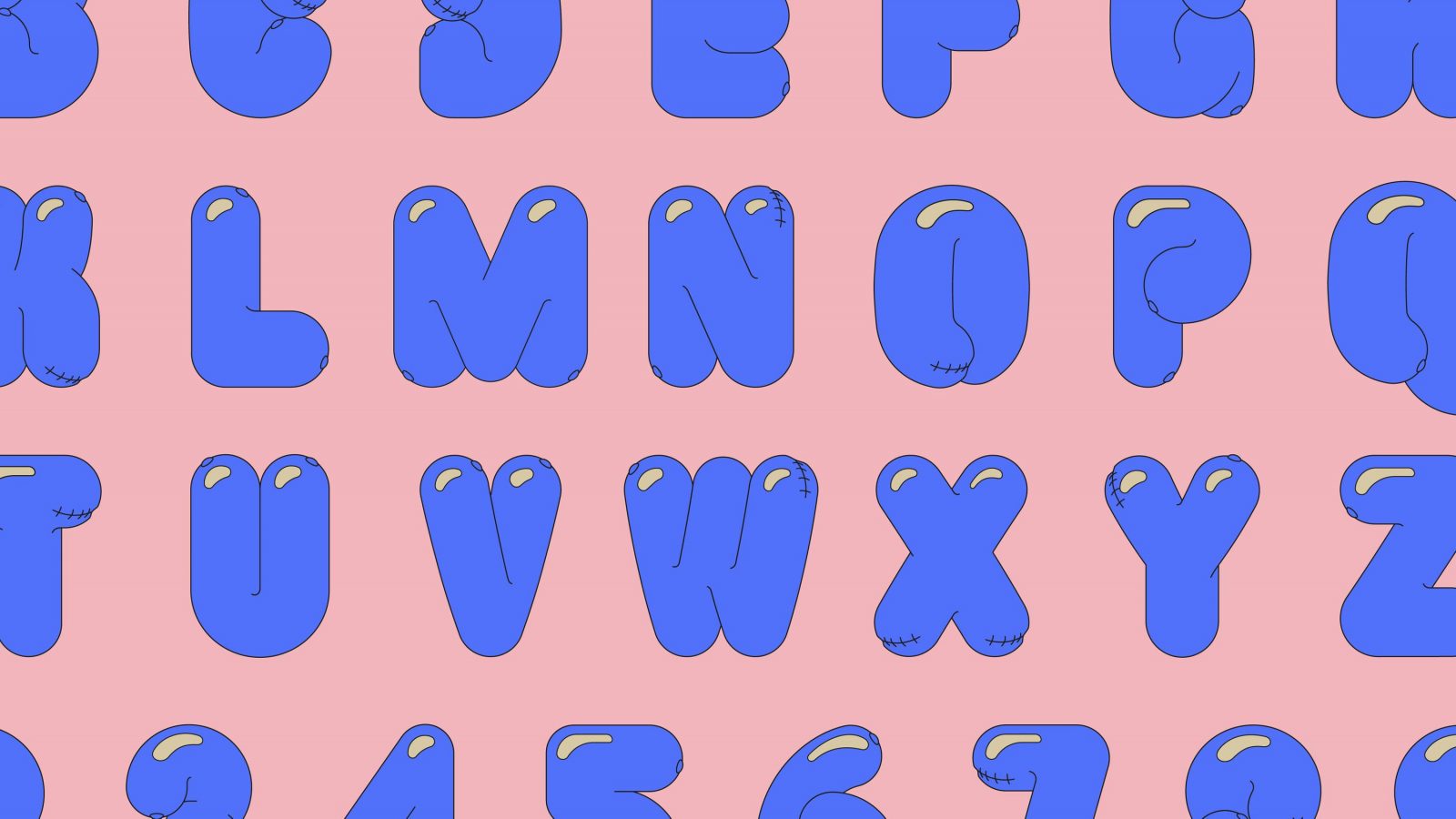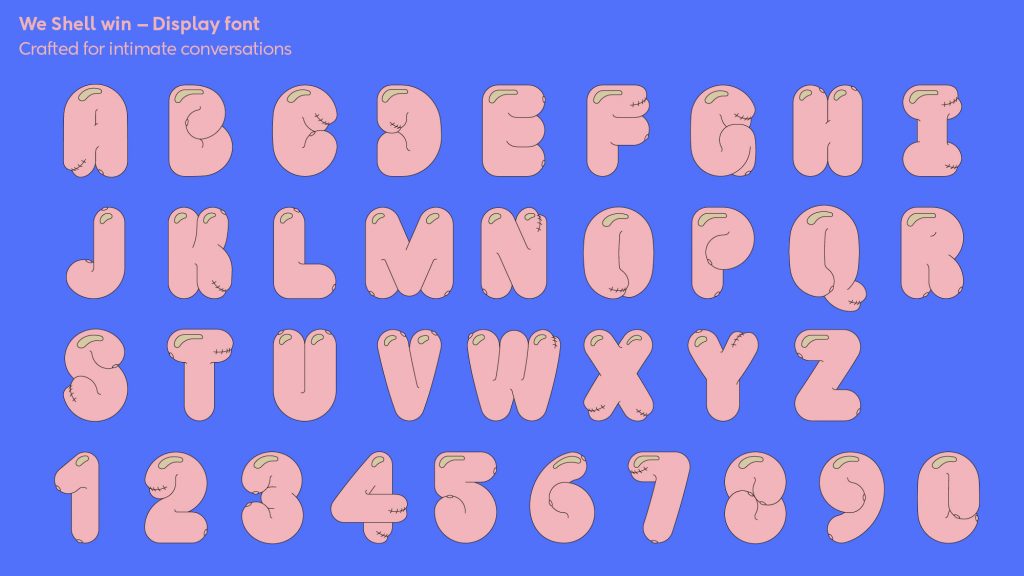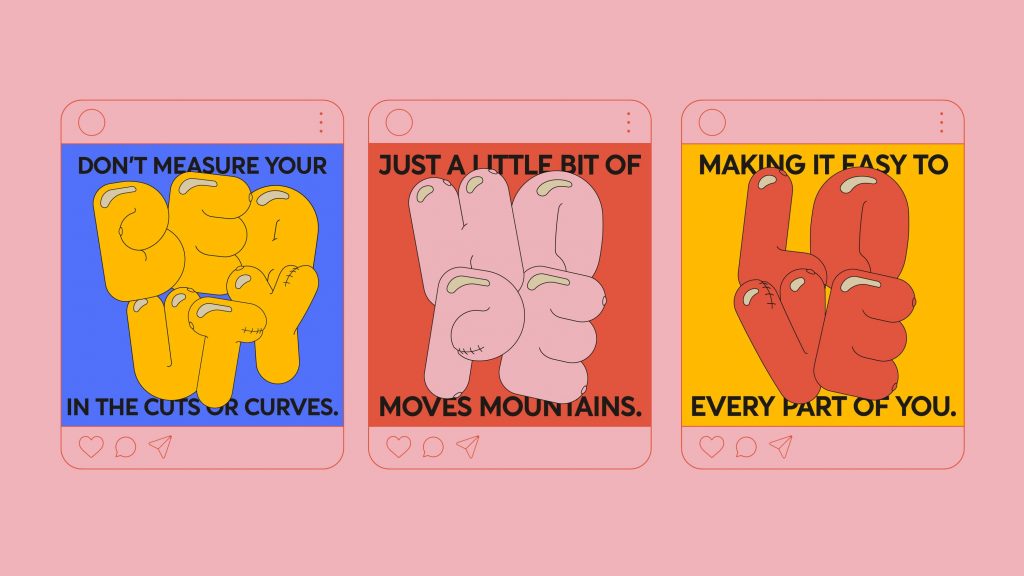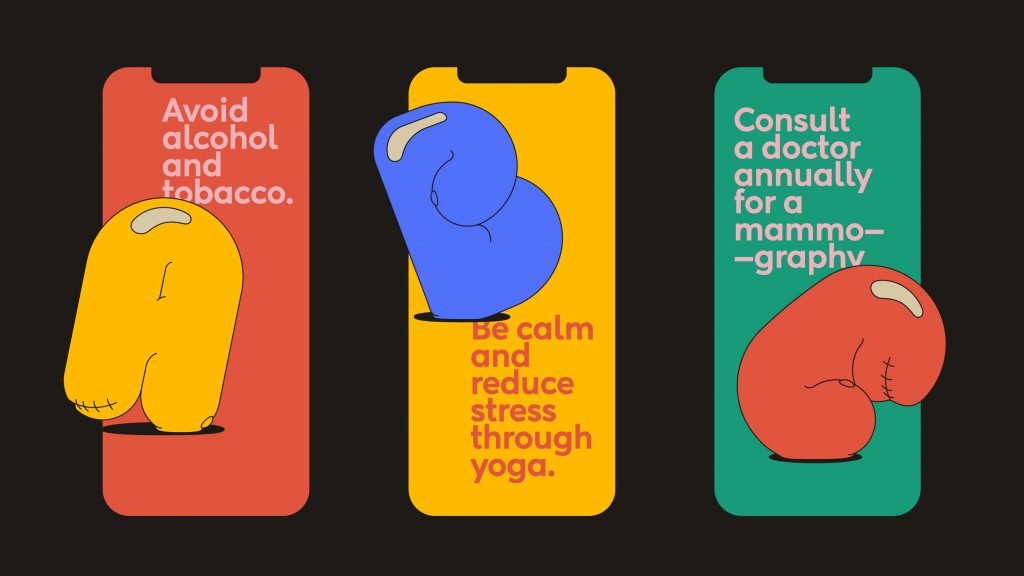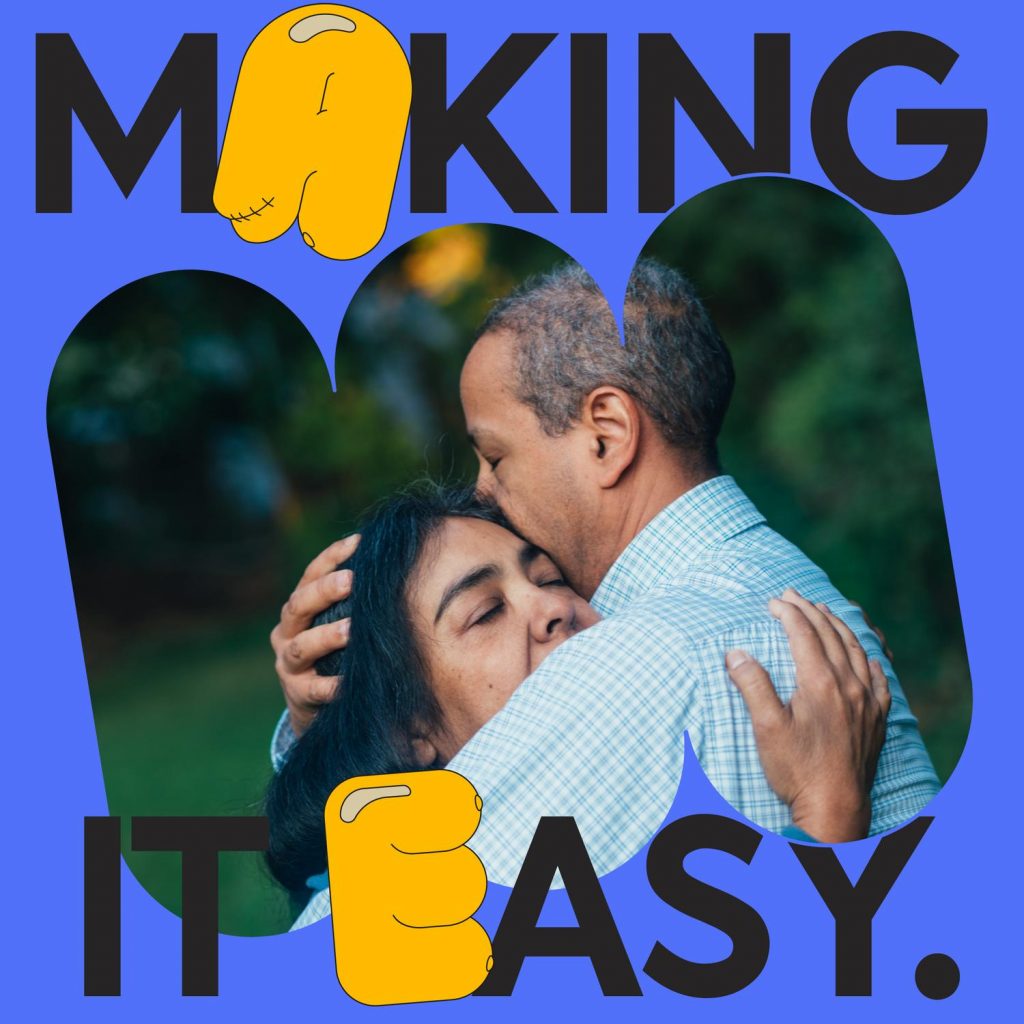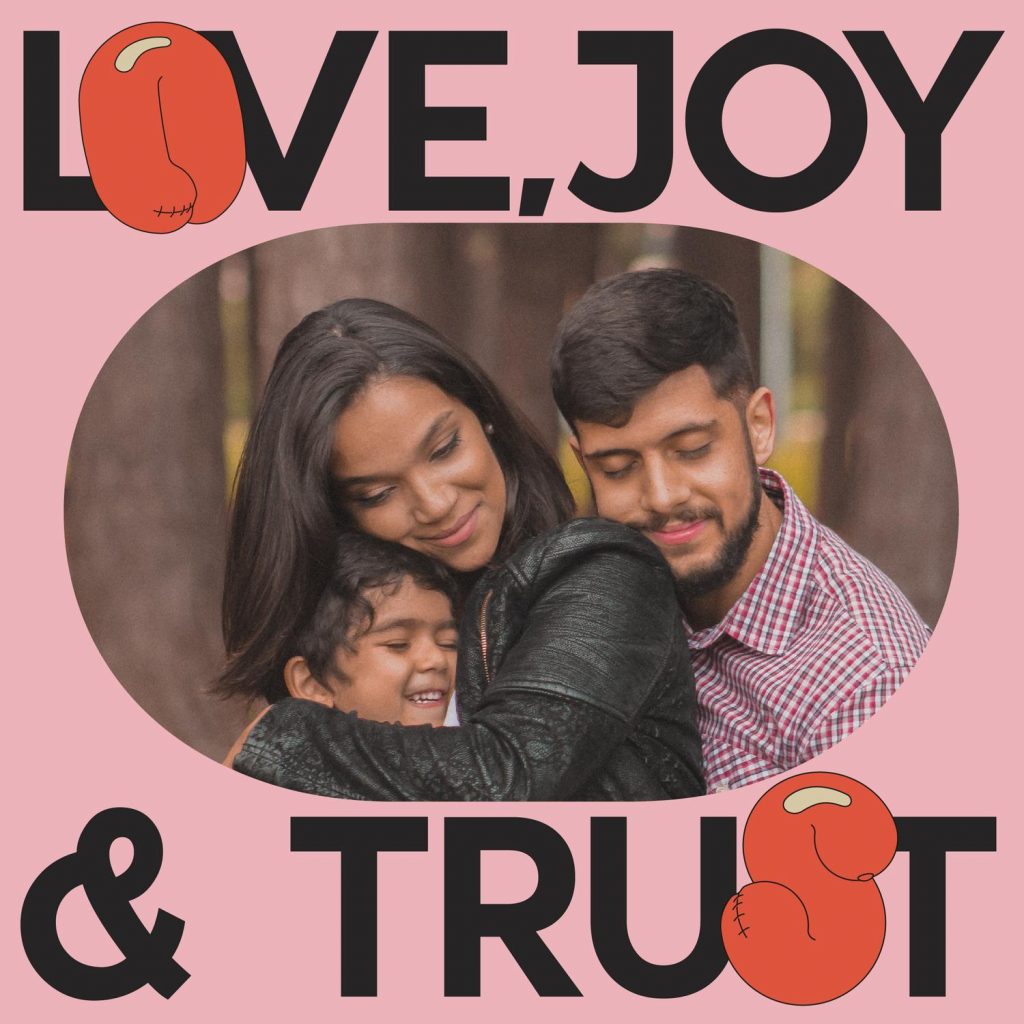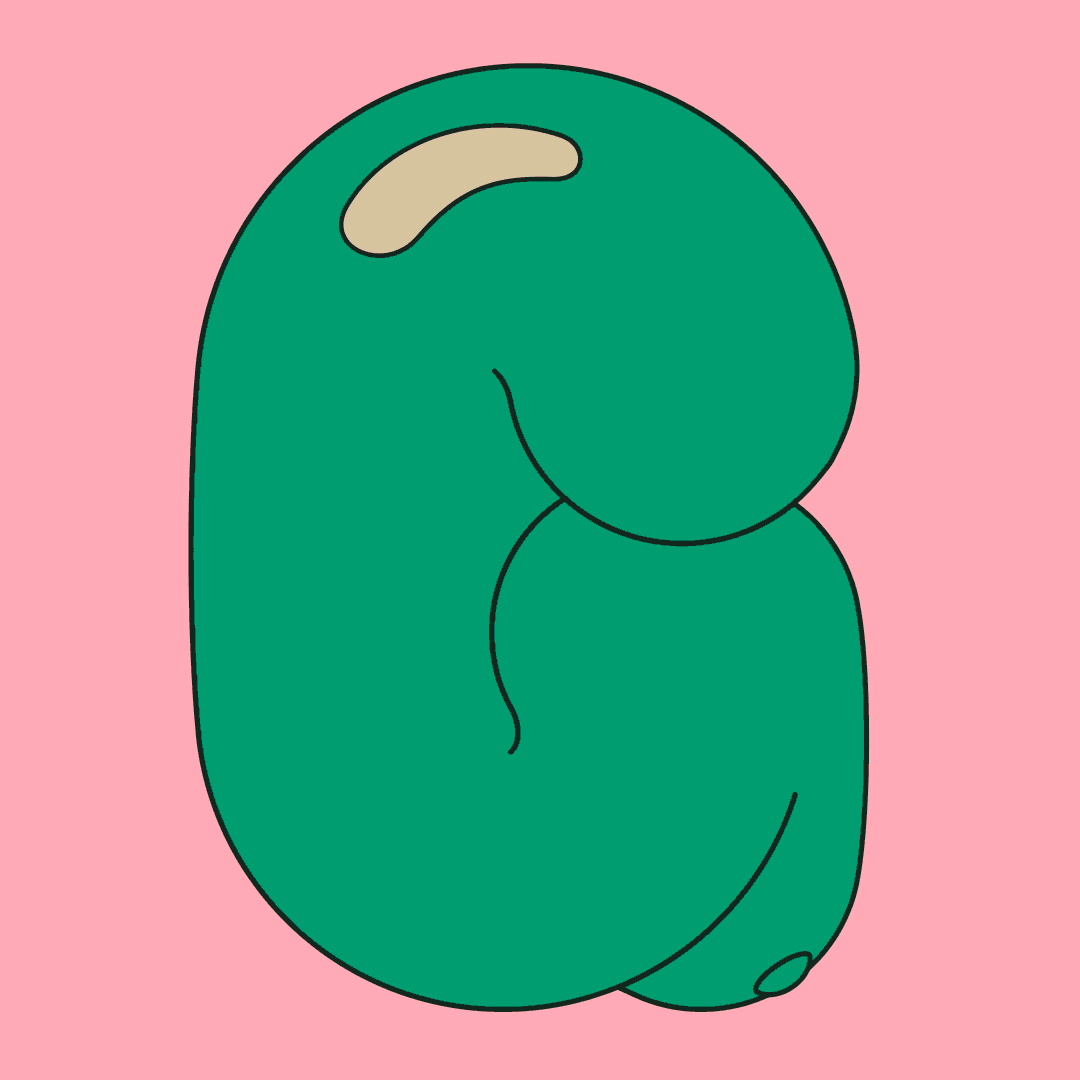
Shell Win, một tổ chức từ thiện về bệnh ung thư vú có trụ sở tại Ấn Độ vốn cung cấp hỗ trợ y tế và tài chính cho những phụ nữ trẻ mắc bệnh này, đã hợp tác với studio thiết kế địa phương The House of Two để thiết kế lại thương hiệu của mình, bao gồm các hình minh họa và kiểu chữ (typeface) độc đáo giúp nâng cao nhận thức và gây sự chú ý về chủ đề này.
Tổ chức muốn có một bộ nhận diện thương hiệu mới để đi đôi với kế hoạch chuyển trọng tâm sang nghiên cứu xem xét “nguyên nhân” của căn bệnh này.
Siddharth Khandelwal, người sáng lập The House of Two, cho biết mặc dù là dạng ung thư có thể điều trị được nhất, thế nhưng ung thư vú vẫn là một trong những căn bệnh ung thư phổ biến nhất ở nước này. Nguyên nhân chính là do nhận thức hạn chế, cùng với việc thiếu các hệ thống hỗ trợ và những điều cấm kỵ của xã hội, đã khiến hành trình phục hồi trở nên “cực kỳ đau thương” đối với nhiều phụ nữ và gia đình họ.
Để mở ra “một không gian trung thực và thân mật”, studio đã nghĩ ra một phông chữ riêng có tên ‘We Shell Win’ với các chi tiết tinh tế được thiết kế giống như bộ ngực nhằm khuyến khích các cuộc thảo luận về chủ đề này.
Đơn cử dễ thấy nhất đó chính là dạng tròn của kiểu chữ, gợi nhớ đến các bộ ngực cùng chi tiết những vết sẹo mà những người sống sót phải mang. Ví dụ, chữ ‘Y’ mô tả một bên ngực bình thường và một bên có mô sẹo.
Kiểu chữ mang lại cảm xúc “nhẹ nhàng đầy quan tâm” được hy vọng sẽ truyền cảm hứng trao quyền cho phụ nữ và bình thường hóa những thay đổi khó khăn xảy ra với cơ thể họ khi phải chiến đấu với bệnh tật, đồng thời chống lại sự kỳ thị mà họ phải đối mặt khi giao tiếp với cộng đồng.
Ngoài kiểu chữ, tổ chức cũng cho thay mới những hình vẽ minh hoạ của mình theo phong cách vui tươi giống truyện tranh, với bộ ngực được kết hợp vào mỗi thiết kế, truyền tải thông điệp sức khỏe bộ ngực nên là một phần của cuộc trò chuyện hàng ngày.
Khandelwal giải thích rằng những bức vẽ này, mặc dù có thể nhạy cảm với hoàn cảnh của những người mắc bệnh, nhưng vẫn đủ nhẹ nhàng và sống động để “xóa bỏ sự xấu hổ và cấm kỵ” khi nói về chủ đề này trước công chúng.